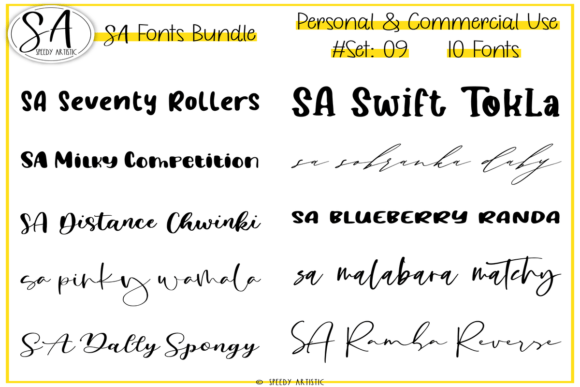
Script and Handwritten Bundle 9
Trouver les bons éléments de conception peut être un défi, mais Script and Handwritten Bundle 9 propose une collection exceptionnelle qui rehausse instantanément votre travail.
Que vous créiez des produits POD (impression à la demande), des invitations de mariage ou des visuels pour les réseaux sociaux, Script and Handwritten Bundle 9 est un choix idéal.